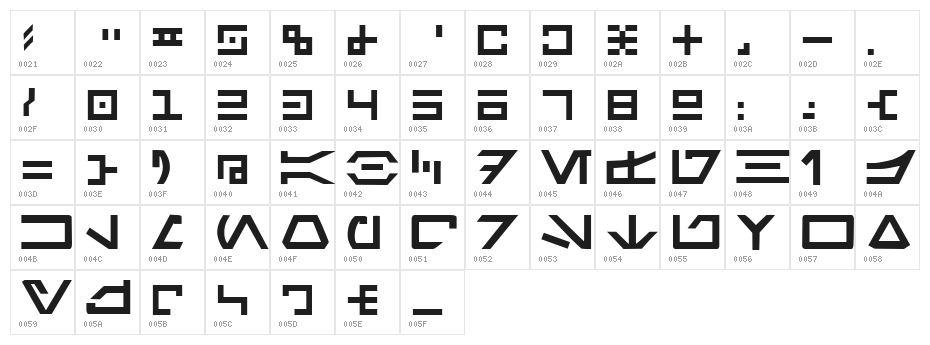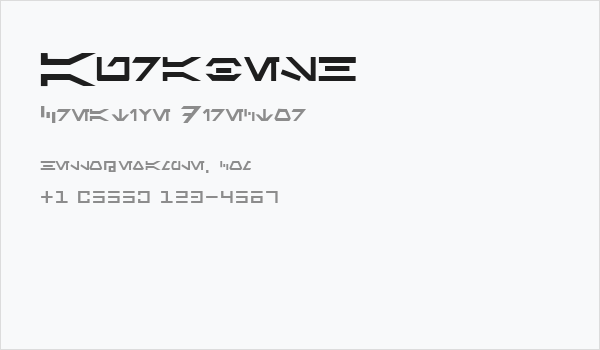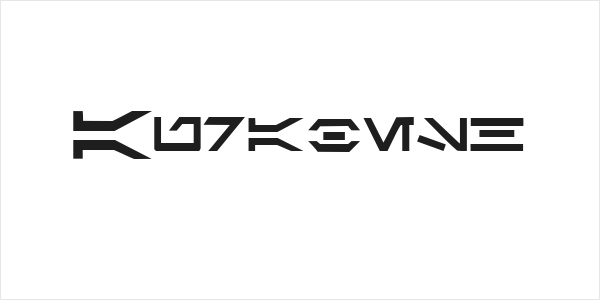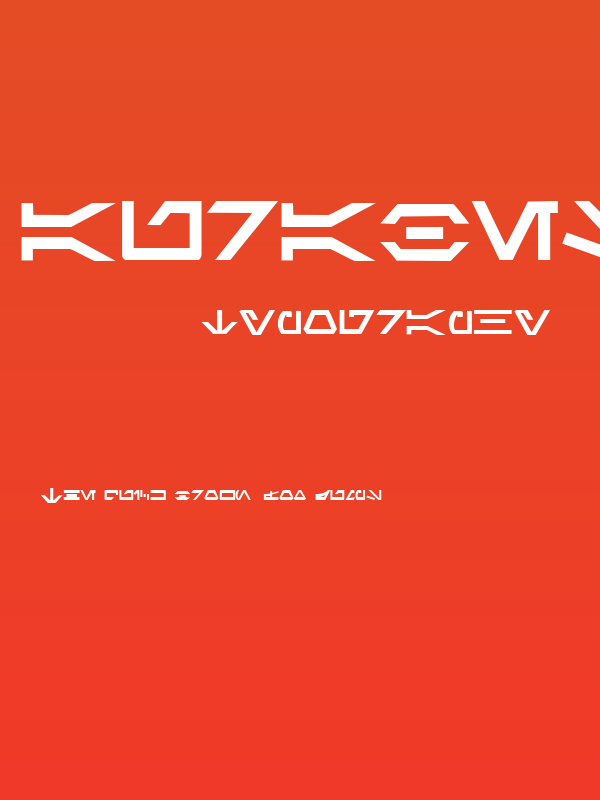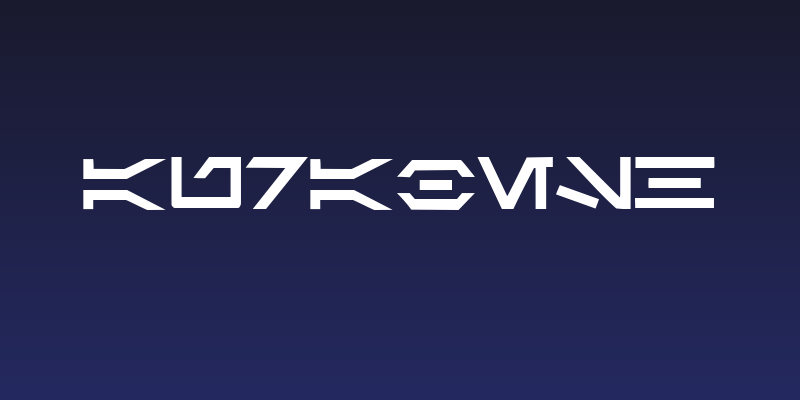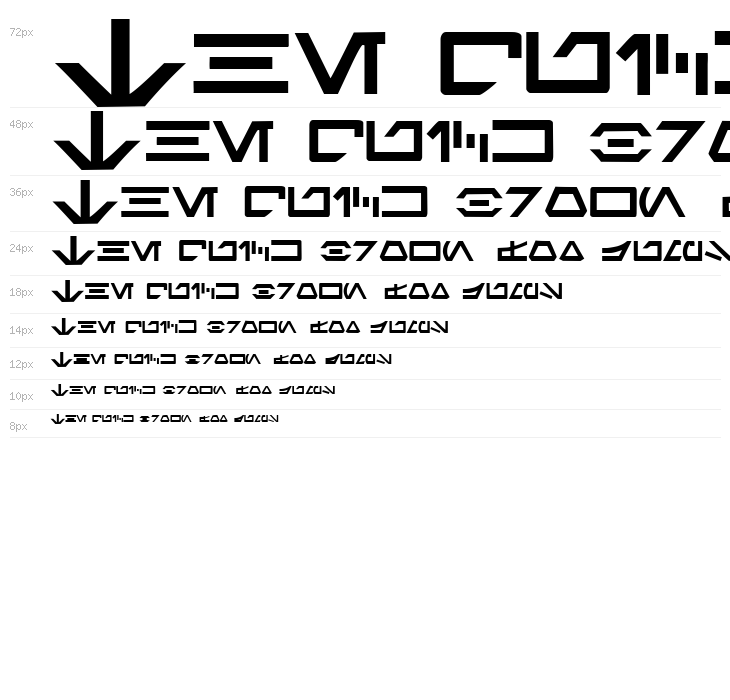
Aurabesh Font
| Gesamtstil | Futuristic |
| Vorgeschlagene Projekte | Ideal for sci-fi themed designs, video game interfaces, movie posters, and branding for tech or futuristic products. |